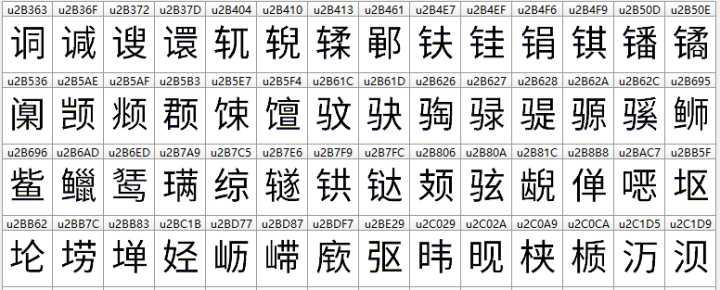
思源宋体 SemiBold字体是一款用于漫画设计方面的字体。
思源黑体是Adobe与Google宣布推出的一款开源字体,有七种字体粗细(ExtraLight、Light、Normal、Regular、Medium、Bold 和 Heavy),完全支持日文、韩文、繁体中文和简体中文,还包括来自 Source Sans 字体家族的拉丁文、希腊文和西里尔文字形共65536个字形。
Google将其命名为Noto Sans JK,作为 Google 的 Noto 字体家族的成员。
Adobe 则命名为 Source Han Sans,作为 Adobe 的 Source 字体家族的一员。
Noto Sans CJK 的风格介于现代和传统之间。设计目标是可以广泛用于多种用途的计算机字体,比如用于手机、平板、或者桌面的用户界面、网页浏览或者电子书阅读等等。